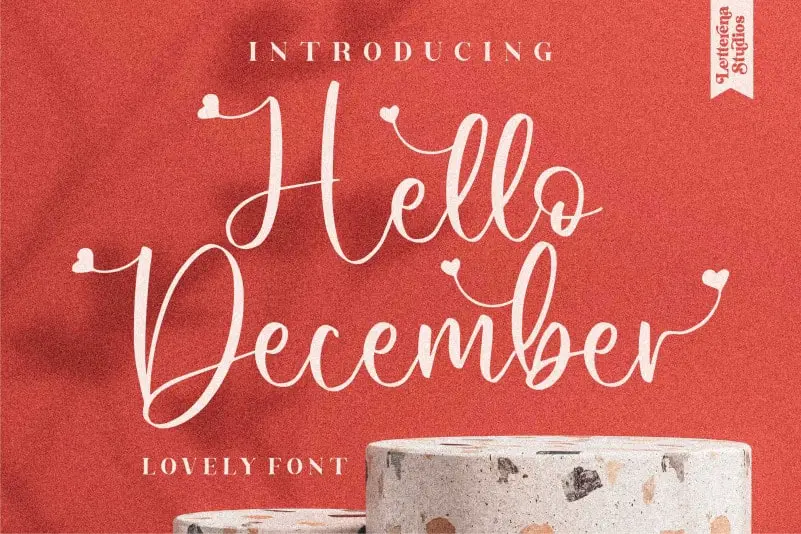
Hello December Calligraphy Font – Download Grátis
A fonte ‘Hello December Calligraphy Font’ é perfeita para quem busca uma escolha elegante e romântica para aniversários de casamento, cartões de Natal ou qualquer projeto criativo que exija um toque especial. Esta fonte escrita a mão flui com facilidade e possui um acabamento suave e rico, garantindo um visual sofisticado sem deixar de ser amigável aos olhos do espectador. Ideal para criar cartões de Natal singelos ou criativos, decorações de natal personalizadas ou até mesmo uma identidade corporativa romântica, ‘Hello December Calligraphy Font’ é a fonte perfeita para qualquer projeto que deseja um ar delicado e misterioso. Ela transmite um encanto especial idealizado para celebrar os finais do ano com amor e carinho.